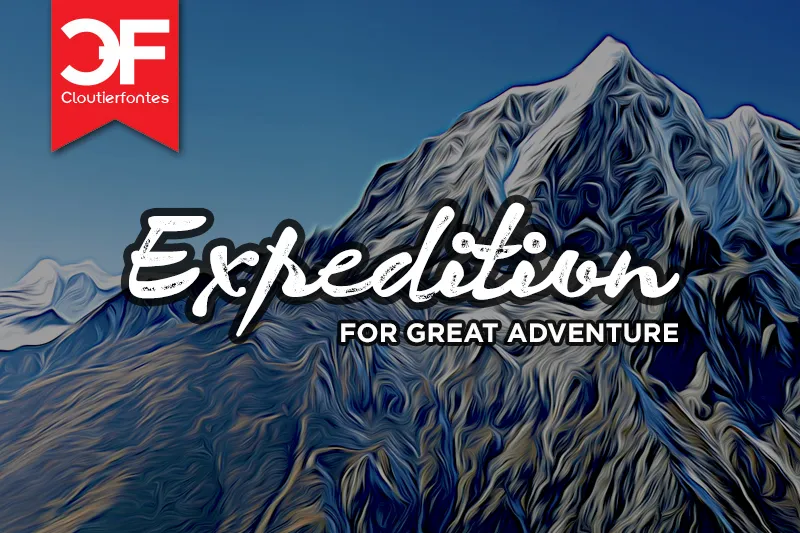
A fonte ‘CF Expedition’ é uma escolha natural para qualquer projeto que busca estilos futuristas e icônicos. Desenvolvida pelo designer Hamilton, esta fonte do tipo Display oferece linhas ergonômicas que se destacam na web e em impressões. Ela é perfeita para criar gráficos impactantes ou levar um projeto a sérvor de alto nível sem comprometer sua personalidade única. A versão gratuita da CF Expedition está idealmente projetada para uso pessoal – não lhe trará receitas diretas. Para quem deseja explorar ainda mais as possibilidades, o designer Hamilton disponibiliza uma versão comercial que inclui um amplo conjunto de caracteres e símbolos adicionalmente personalizados. Você pode conhecer mais sobre essa opção no link: http://www.cloutierfontes.ca/CloutierFontes/Expedition.html.